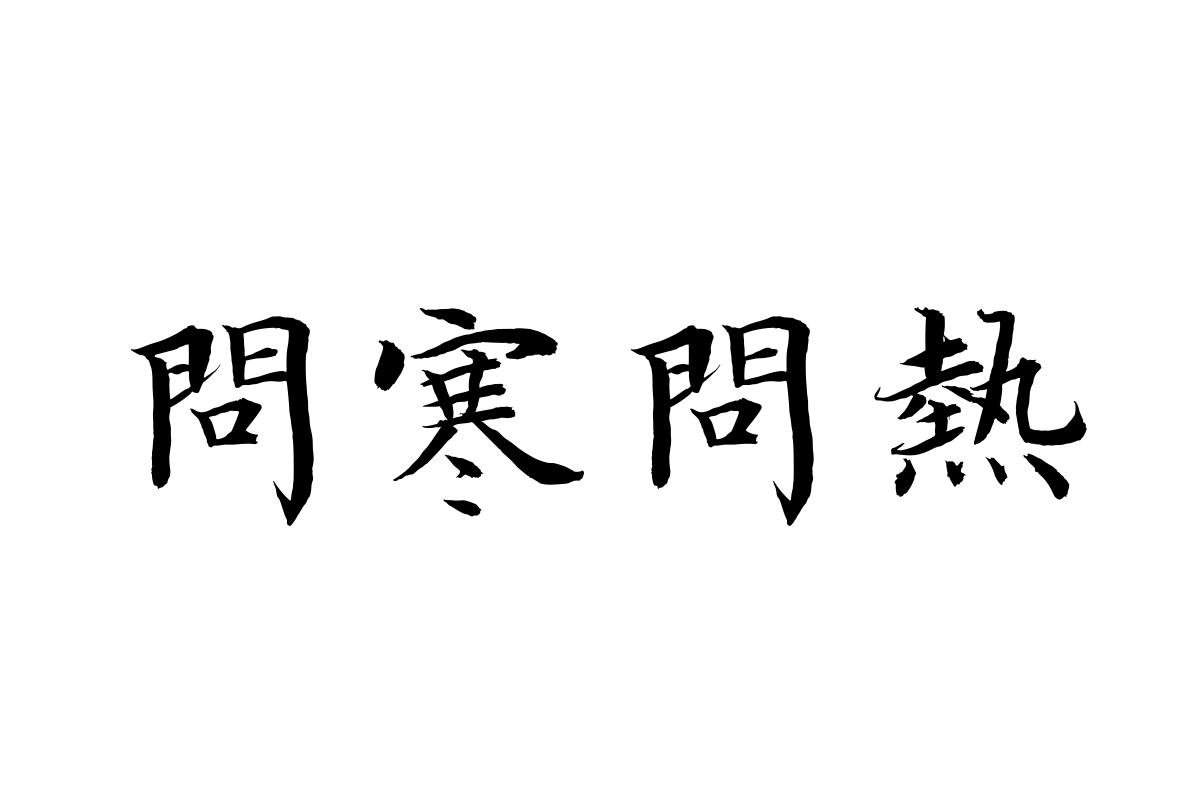
汉仪闫锐敏楷书繁是一套具有深厚文化底蕴的书法字体,它汲取了传统书法艺术的精髓,将现代审美与传统文化完美融合。这款字体以其独特的笔画结构和流畅的线条,展现出一种优雅、大气的美感。
字体特点:
1. 笔画流畅:汉仪闫锐敏楷书繁的笔画线条流畅自然,给人一种舒适、轻松的感觉。
2. 结构严谨:字体的结构严谨,每个字的笔画都经过精心设计,使得整个字体看起来整齐、有序。
3. 风格独特:这款字体的风格独特,既有传统的韵味,又不失现代感,适合用于各种场合的书写和设计。
4. 适用范围广泛:汉仪闫锐敏楷书繁适用于各种场合,如书法创作、平面设计、网页设计等,是一款非常实用的字体。